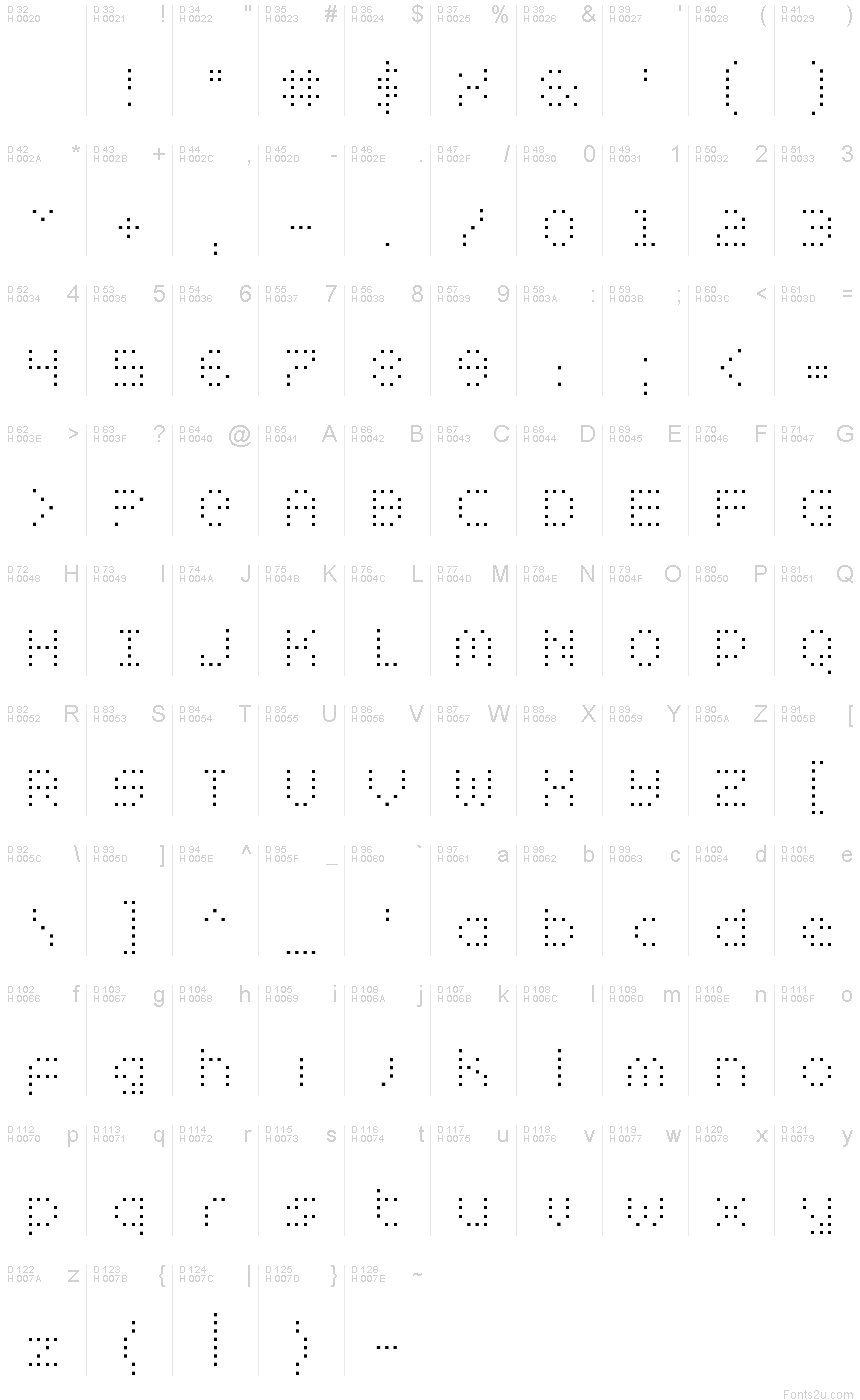
Zado Semi-Condensed to darmowy font bitmapowy od Iconian Fonts, o minimalistycznym, pikselowym wyglądzie, który przywodzi na myśl grafikę z wczesnych ekranów komputerów. Litery zbudowane są z surowych, kwadratowych modułów i krótkich segmentów, co nadaje krojowi sztywny, oparty na siatce rytm, z optymalnym odstępem, dzięki któremu kształty pozostają ostre i lekko mechaniczne.
Dzięki temu idealnie sprawdza się w brandingu gier retro, ekranach powitalnych, plakatach sci-fi, zinach i kompaktowych tytułach, gdzie darmowa czcionka ma nadać klimat niskiej rozdzielczości, nie tracąc przy tym na wyrazistości. Świetnie sprawdza się również w krótkich nagłówkach i etykietach menu, ponieważ zwarta, blokowa konstrukcja sprawia, że przekaz jest uderzający i jednoznacznie cyfrowy.